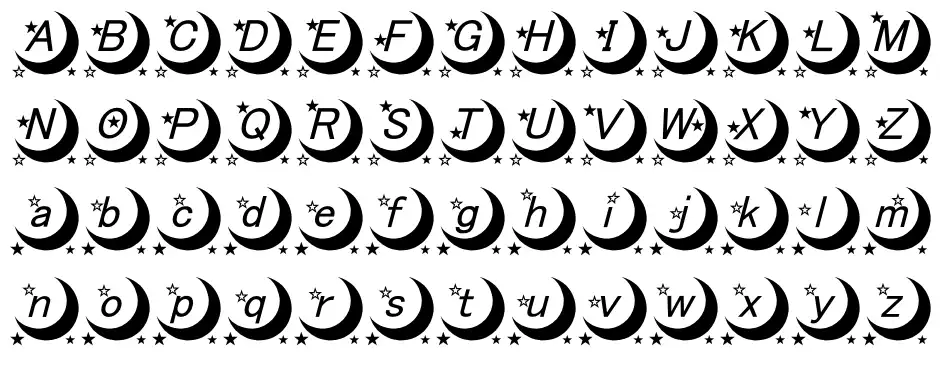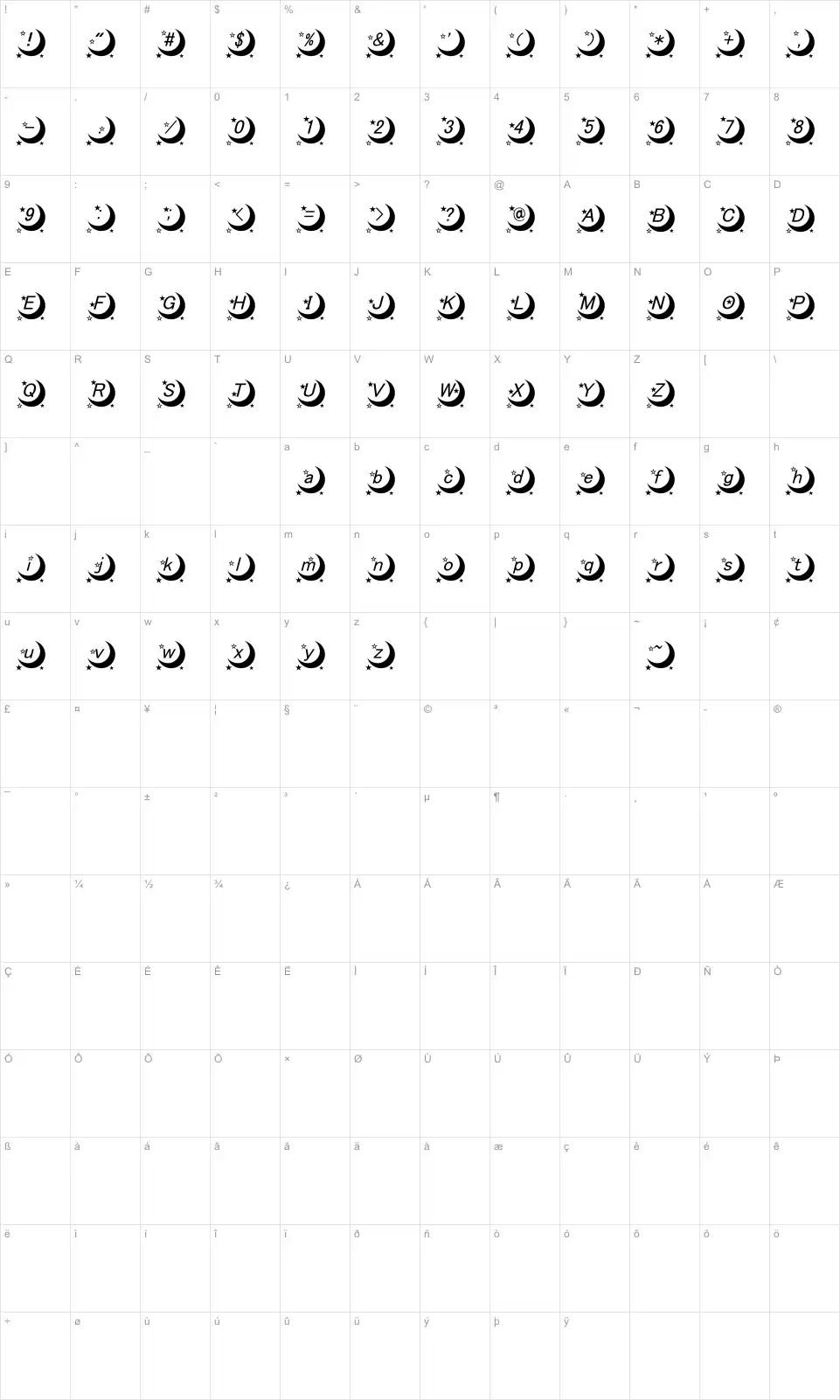
Descubra o encanto da fonte Moon Font, projetada pela TamaFactory. Esta elegante fonte de categoria Fancy oferece um toque sofisticado e decorativo para seus projetos. Se você está à procura da Moon Font, agora é o momento de descobrir sua versão completa. Com apenas alguns cliques, você pode baixar a fonte ou gerar um visual personalizado online para ver como ela se assemelha em seu projeto antes de usá-la. A fonte Moon Font é gratuita e em formato TTF, o que a torna facilmente utilizável em qualquer projeto digital. Desde sua adição em 2022-07-12, a fonte já foi baixada pelo menos 2386 vezes, demonstrando seu valor e popularidade. Com seu tamanho de apenas 9 KB, é uma escolha ótima para projetos de baixo espaço de armazenamento. Visite a página oficial da TamaFactory para mais detalhes e inspiração.
Categoria: Fancy › Decorative
Designer: TamaFactory